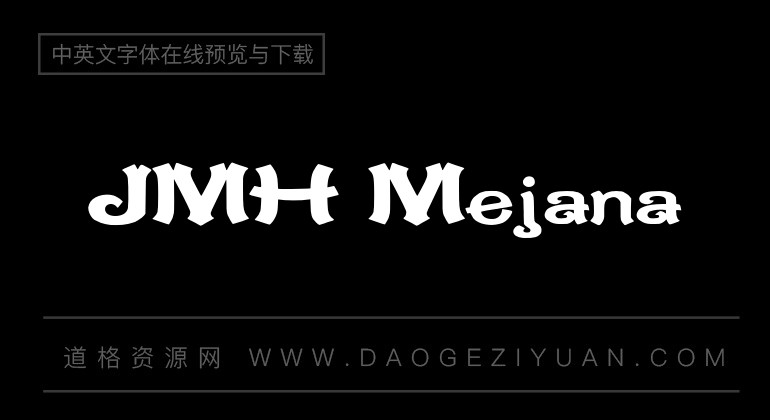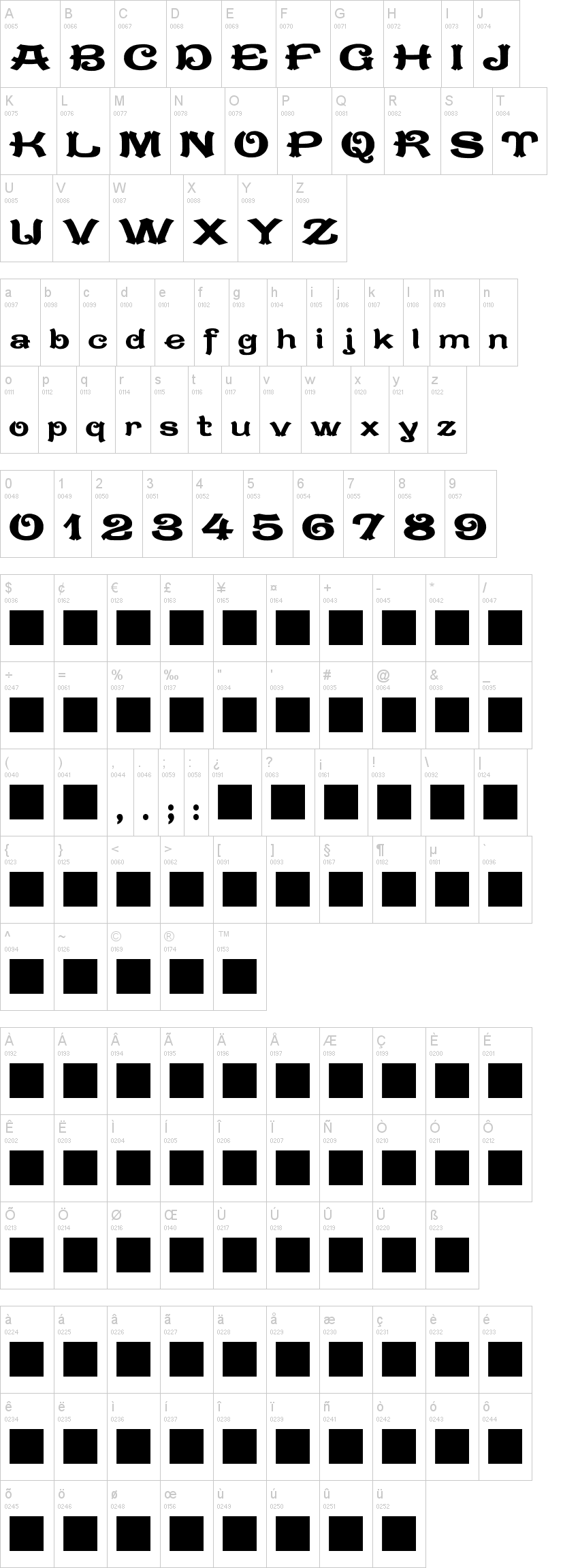
JMH Mejana 是一款来自摩洛哥的蒙古族字体,它是由蒙古族艺术家 JMH Mejana 创作的。它是一款清新的蒙古族字体,具有漂亮的线条和流畅的形状。它的字体特点是拥有鲜明的线条,清晰的字形,以及简洁的外观,使它能够很好地表达蒙古族文化的精髓。它是一款适合用于文字、图形和排版的字体,适用于各种文档和印刷品。内容介绍
JMH Mejana是一款非常不错的手写艺术字体,具有很好的视觉感,适合于文化类的宣传设计、商业类品牌的广告和产品包装设计以及个性化文字排版等较多场景。